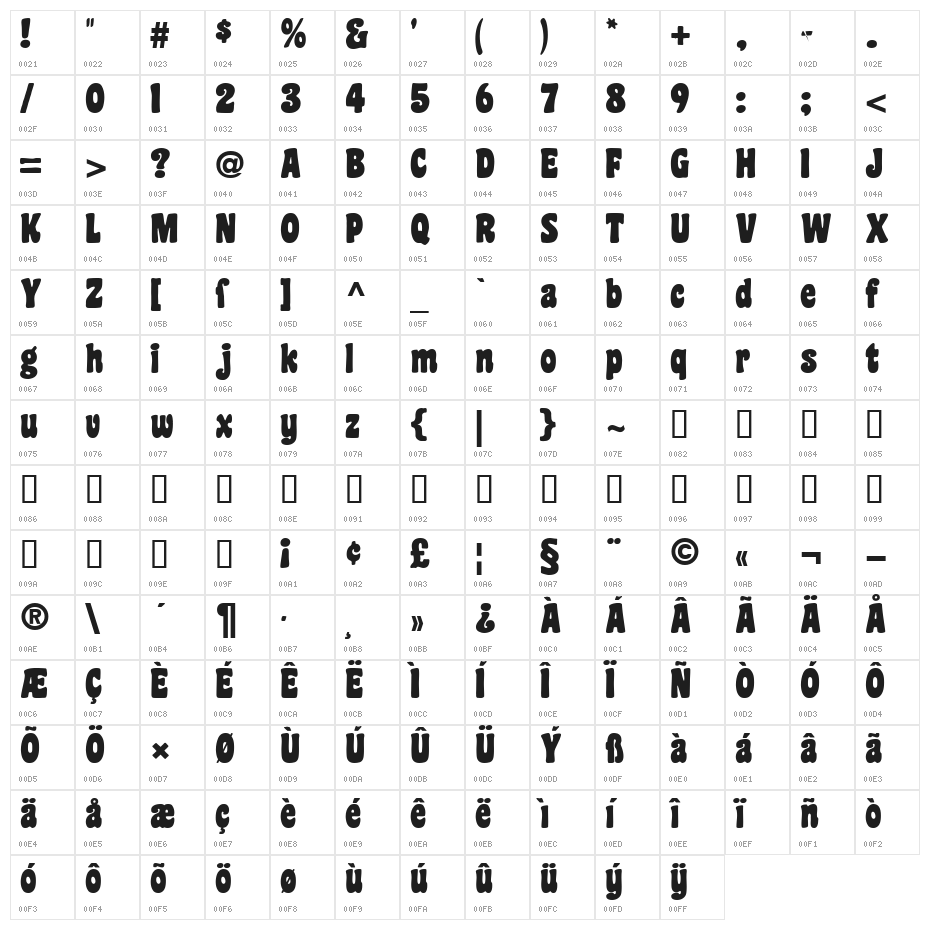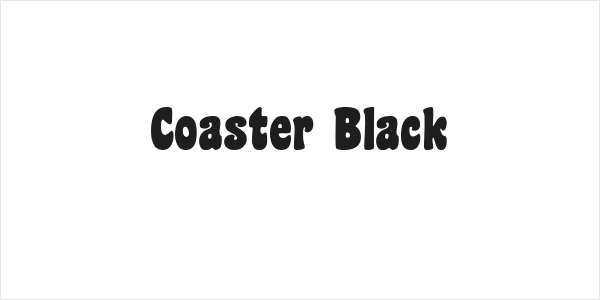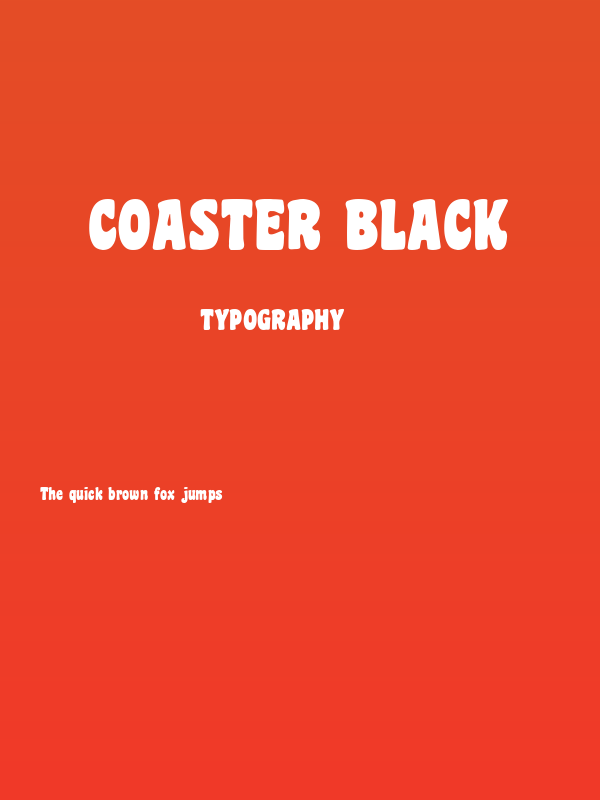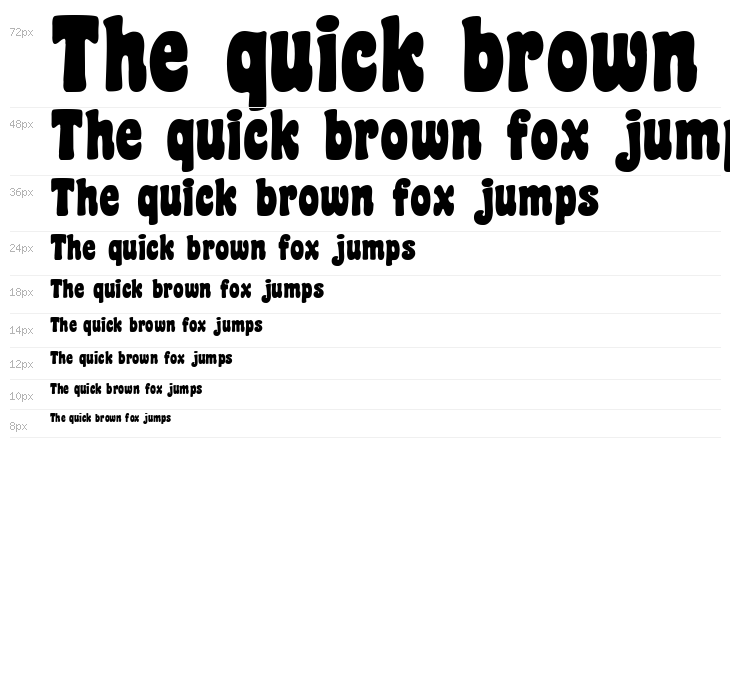
Coaster Black Font
Fonts by Dieter Steffmann
| 整体风格 | Vintage |
| 推荐项目 | Ideal for vintage-themed posters, playful branding, children's books, and eye-catching headlines. |